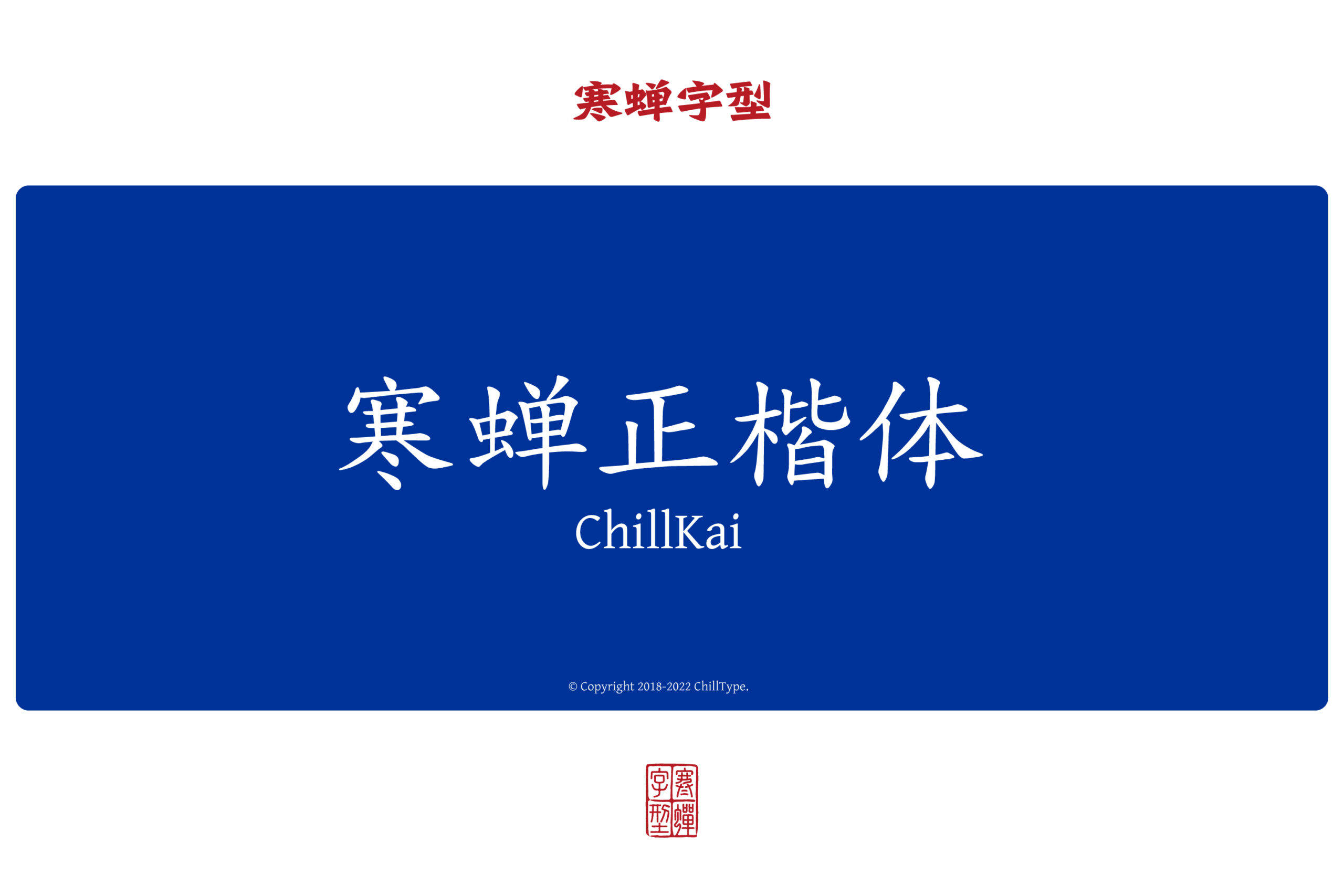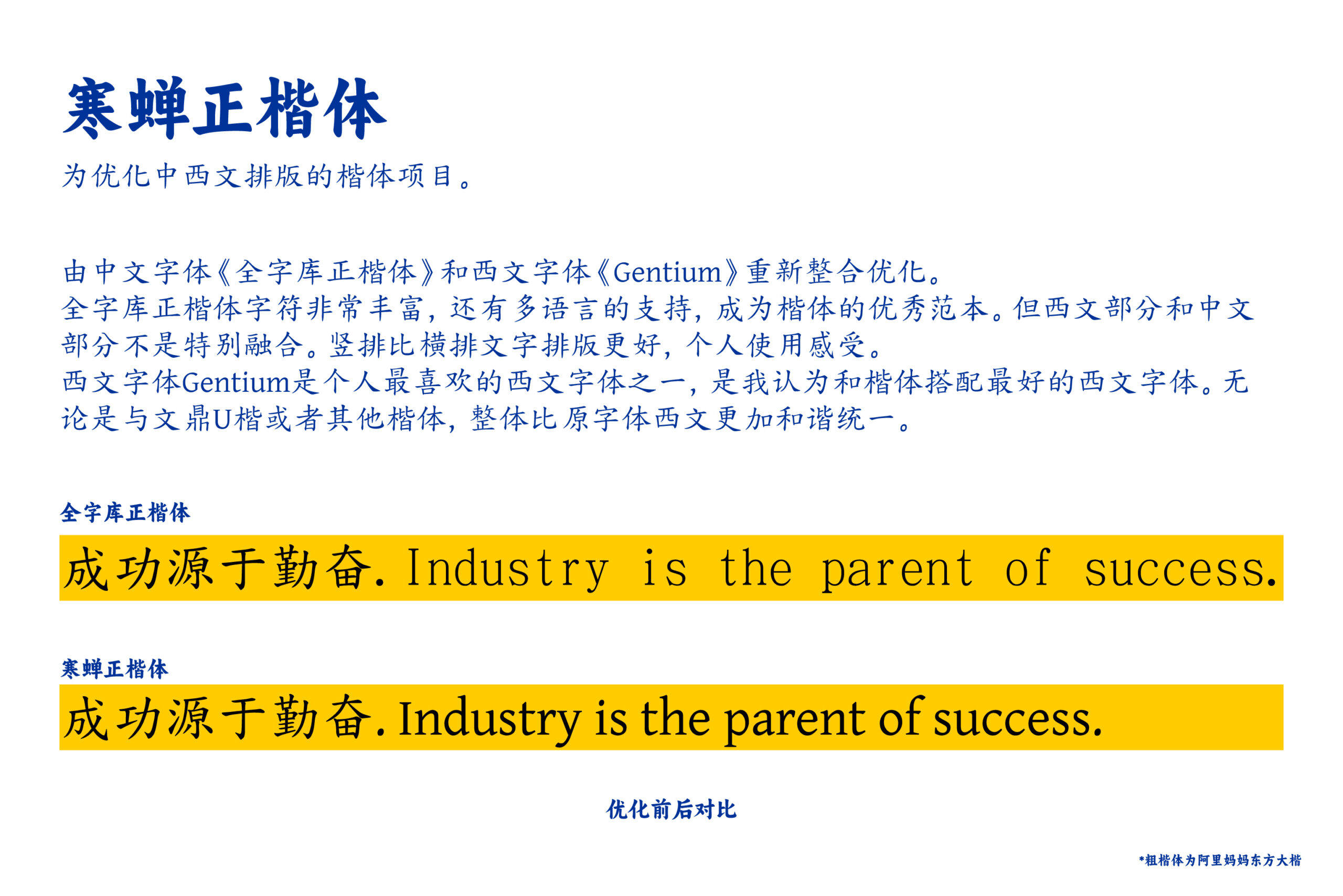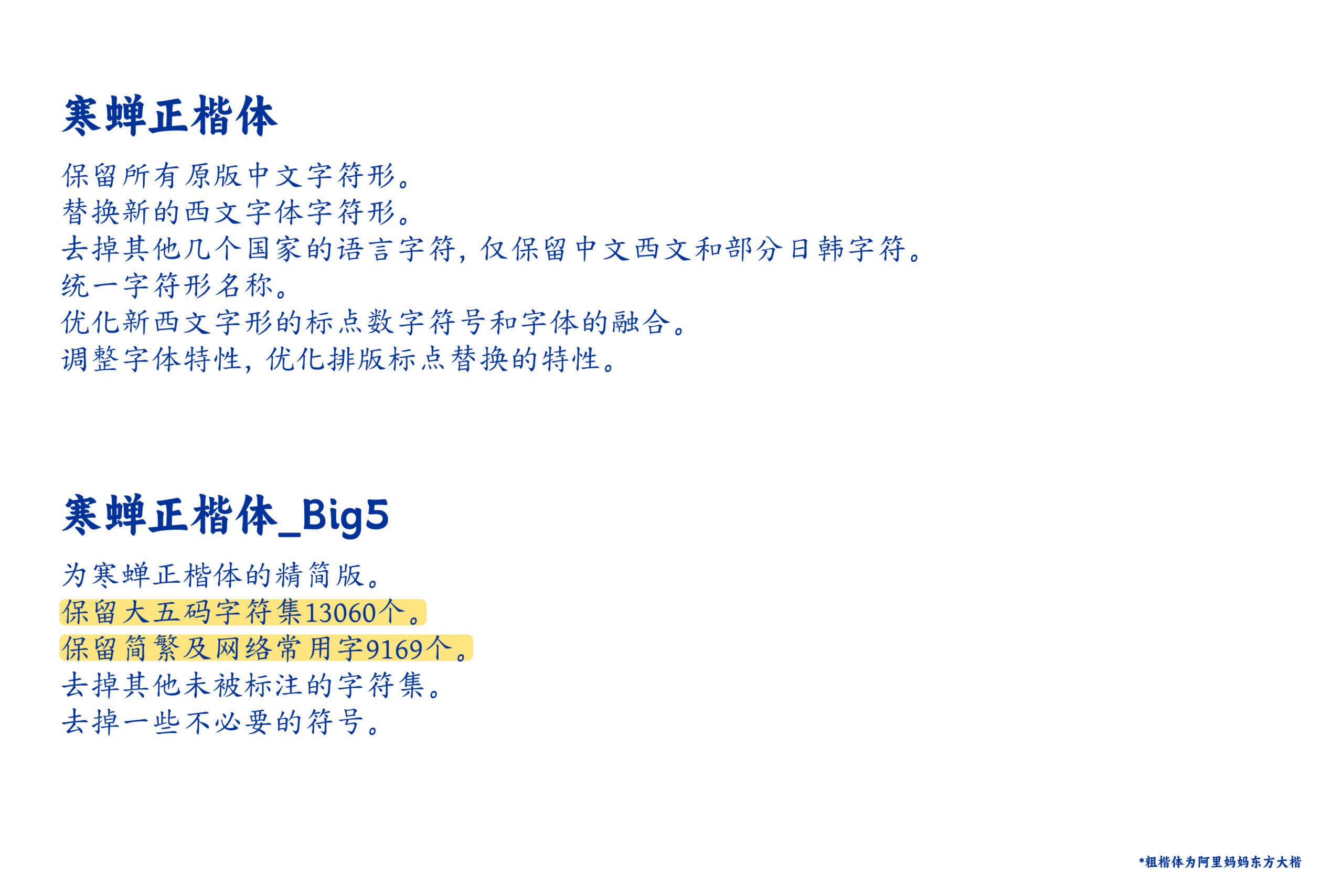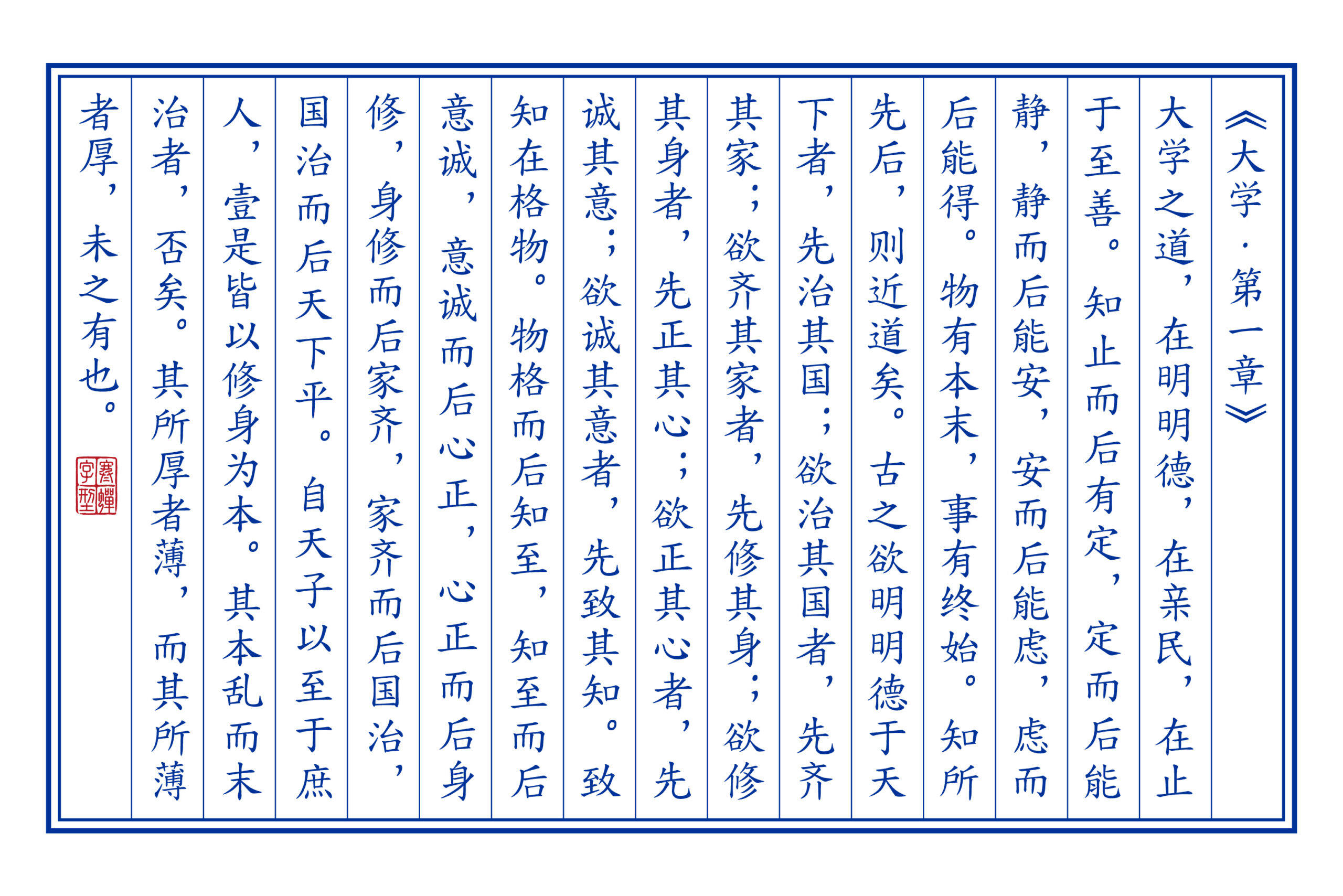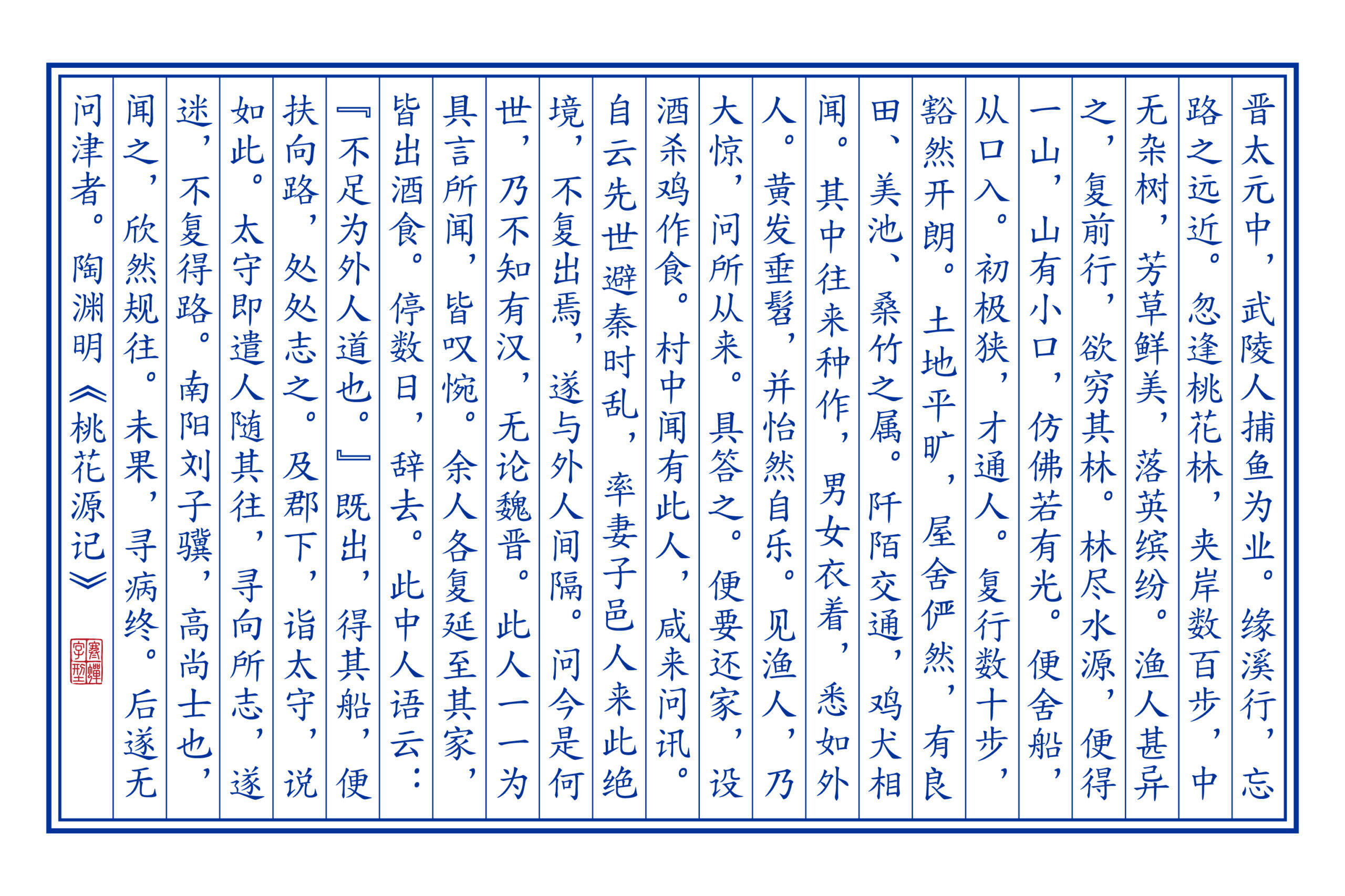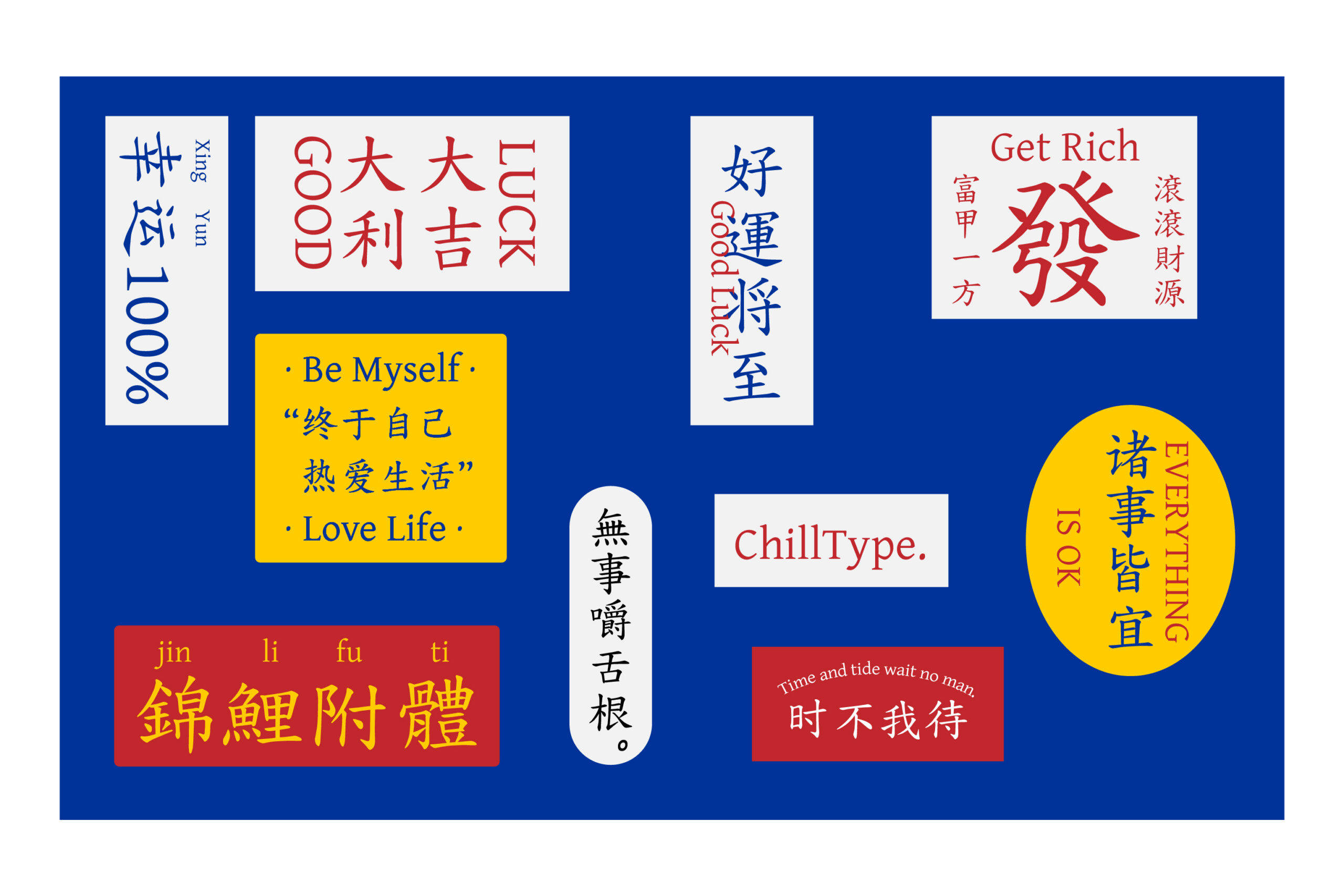
寒蝉正楷体是一款经过精心整合与优化的定制字体,它将中文字体《全字库正楷体》与西文字体《Gentium》进行了创新的结合。《全字库正楷体》本身字符集极其丰富,涵盖了大量汉字及多语言字符,其严谨规范的笔画结构堪称楷书的优秀范本,为中文部分奠定了坚实的基础。然而,原版字体在中文与西文的搭配上稍显生硬,视觉融合度有待提升。尤其在采用竖排版式时,中西文的衔接效果往往不如横排自然流畅,这是在使用过程中的一些个人体会。 西文部分选用的《Gentium》字体,是由字体设计师Victor Gaultney所设计的一款杰出作品,它结构优雅、比例协调,具有文艺复兴时期的书法美感。这款字体本身就被广泛认为是兼具古典气质与现代可读性的典范之一。在《寒蝉正楷体》中,经过细致的字形调整与度量匹配,Gentium与全字库正楷体的融合度达到了很高的水平,实现了中西文在视觉节奏与灰度上的和谐统一。 这种搭配不仅超越了原版全字库正楷体自带的西文部分,更在实际排版中展现出优异的整体性。无论是相较于文鼎U楷、汉仪楷体,还是其他常见的楷体字族,寒蝉正楷体所呈现的中西文混排效果都更为协调与优美,尤其适用于长篇阅读、标题设计或需要中英对照的出版物场景,极大地提升了版面的专业感与视觉舒适度。